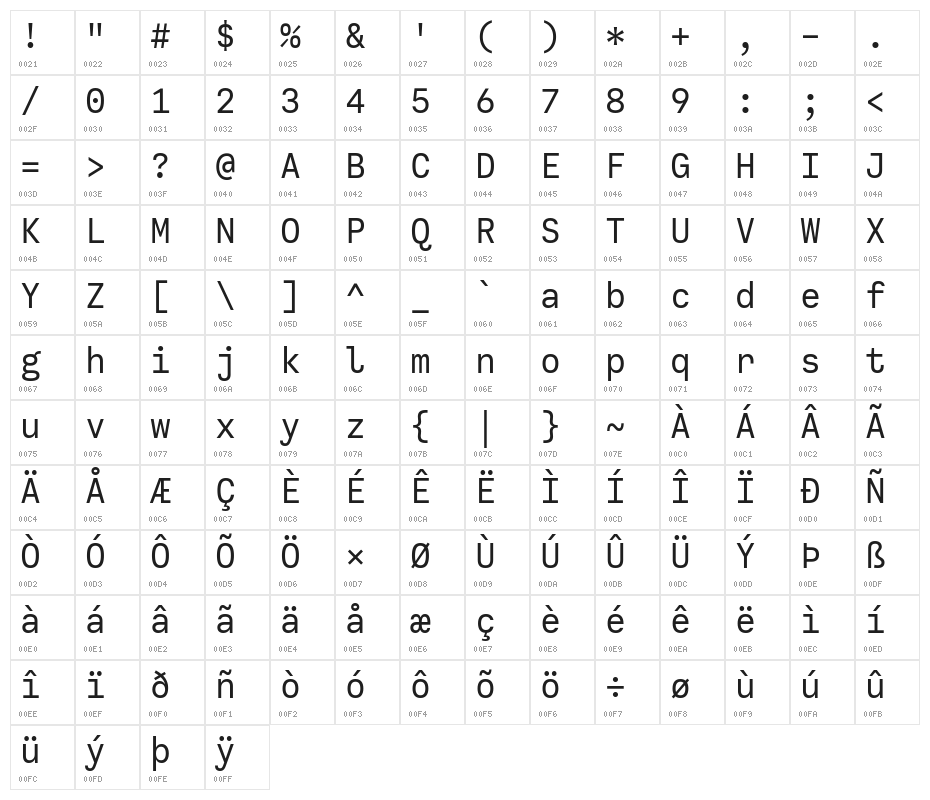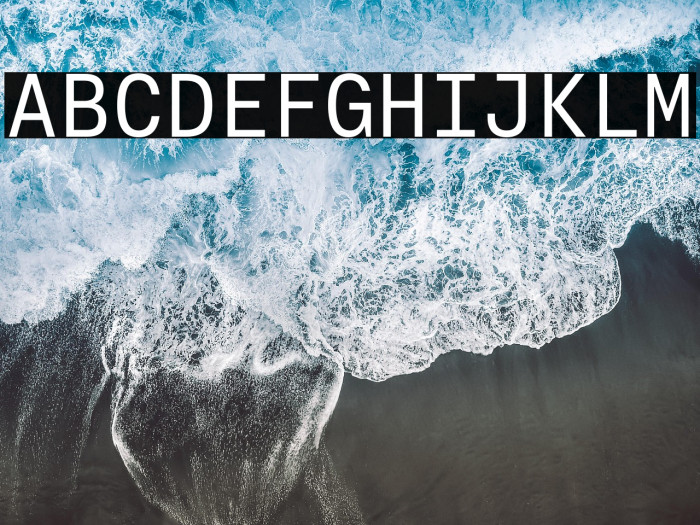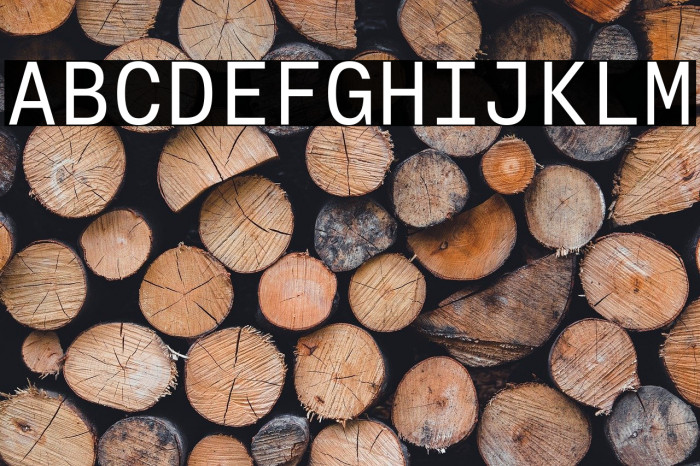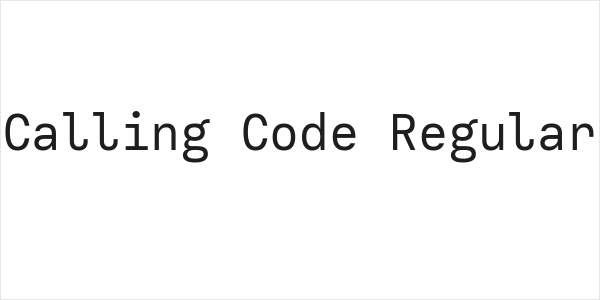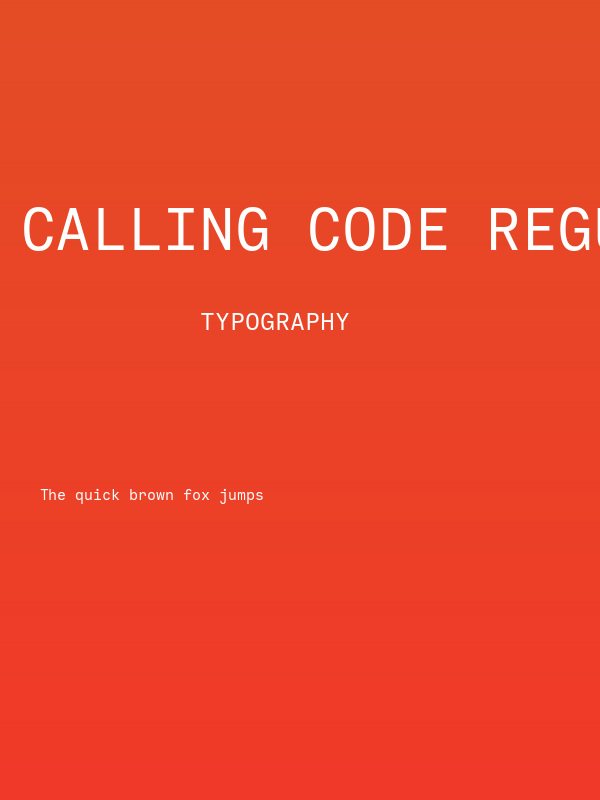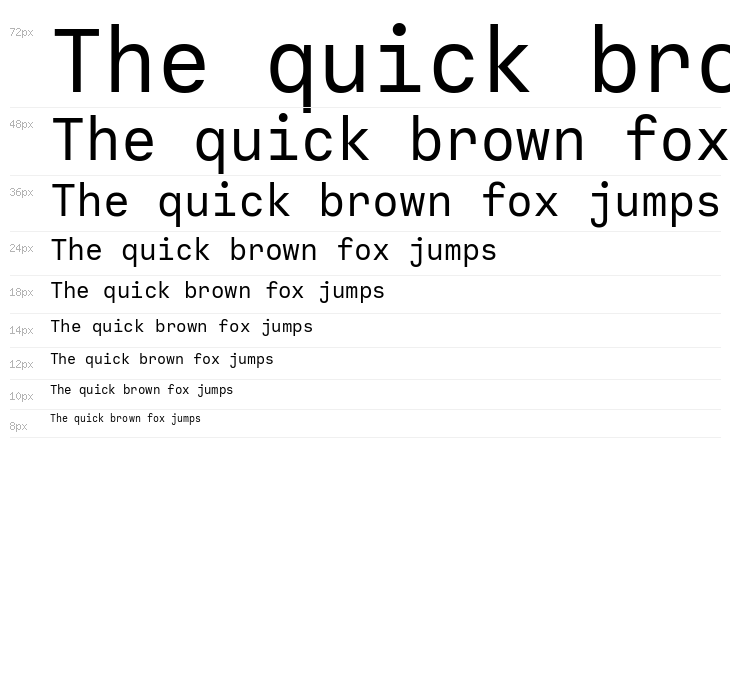
Calling Code Regular Font
| おすすめプロジェクト | Ideal for digital interfaces, branding, signage, and editorial design where clarity and modernity are key. |